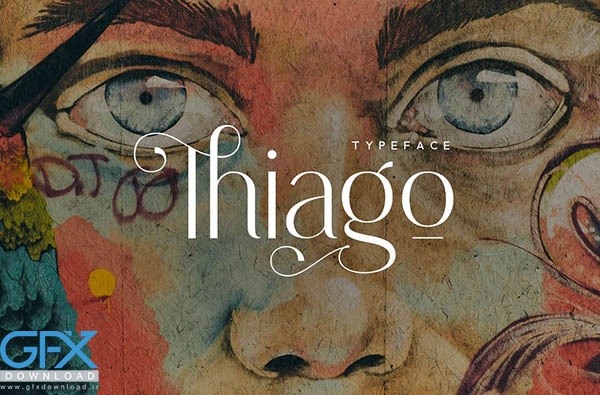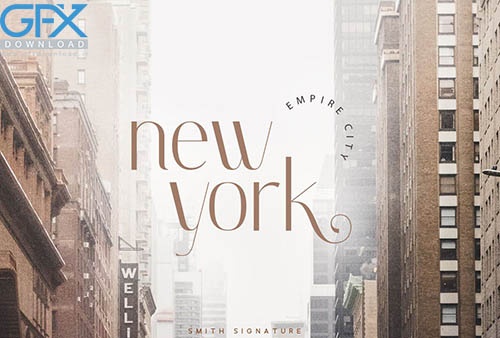
دانلود رایگان فونت Thiago
دانلود رایگان فونت مدرن Thiago
دانلود رایگان فونت مدرن انگلیسی Thiago
Thiago یک خانواده فونت مدرن sans serif است، تک تک حروف با دقت ساخته شده اند تا متن شما زیبا به نظر برسد. این فونت شامل علامت متنی زیبا است. شما می توانید از طریق Font Book (کاربر مک) یا نقشه کاراکتر ویندوز (کاربر ویندوز) به علامت جایگزین دسترسی داشته باشید، آموزش پیوند در داخل فایل فشرده قرار داده شده است. برای دانلود رایگان فونت Thiago از جی اف ایکس دانلود به ادامه مطلب مراجعه کنید.
فونت انگلیسی Thiago